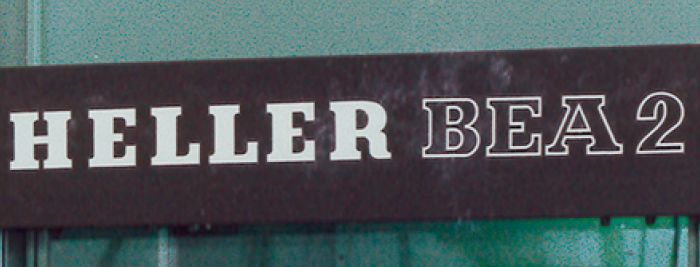
Ich suche diese Slab Schrift, 70er/80er, Fotosatzschrift?
kann mir jemand behilflich sein diese Firmenschrift zu identifizieren?
Trotz ausführlicher Suche habe ich noch nichts passendes gefunden.
Ähnlich sind Lucida Serif, Clarendon, Aachen etc.
Ich vermute sie stammt aus den 70er oder 80er Jahren.
Die beiden Heller-Schriftzüge im Eingangspost sind nicht identisch, das R unterscheidet sich deutlich. Ist nur einer von beiden gesucht?